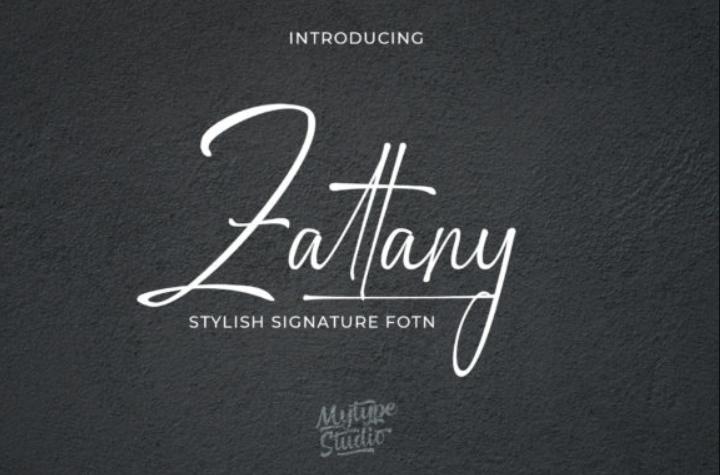
[Creativefabrica] Zattany Font (Mytype Studio)
Zattany - красивый, хорошо сбалансированный шрифт в винтажном стиле. Он отличается плавными изгибами и идеально подходит для модного брендинга или редакционных дизайнов. Добавьте его уверенно в свои проекты, и результат вам понравится.